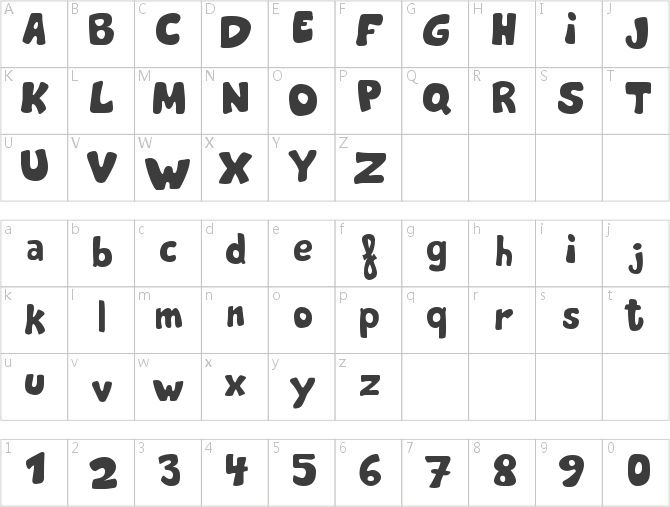
TheKingsoftheHouse-Regular 詳情頁
字體名稱: TheKing
TheKingsoftheHouse-Regular
TheKingsoftheHouse-Regular字體字庫是一款讓人賞心悅目、百看不厭的英文字體,適合各類廣告和產品包裝設計應用,字體大小0.05MB,格式為ttf字體,上傳用戶是woslxn,作者/版權方為未知